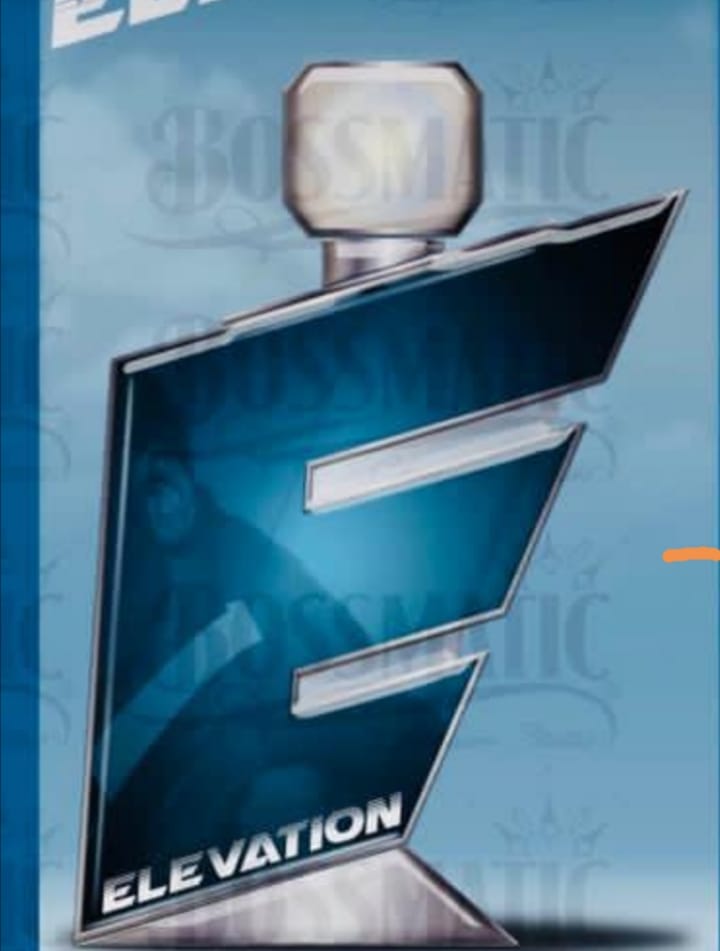
Grafikci Arkadaşlar Bu Yazı tipi hangi Set acaba ?
Arkadaşlar, bu parfüm şisesinin altındaki, elevation'un yazı tipi nedir acaba ? bilgisi olan var ise çok makbule geçecek, fontsquirrel, whatda font vs arattım ama nafile
Bu özelleştirilmiş bir fonta benziyor. Yani benzer bir font bulup özelleştirebilirsin istersen.